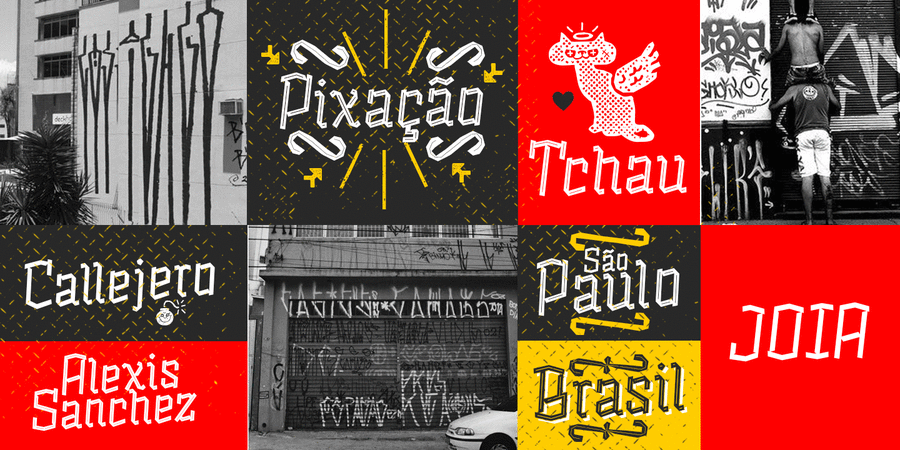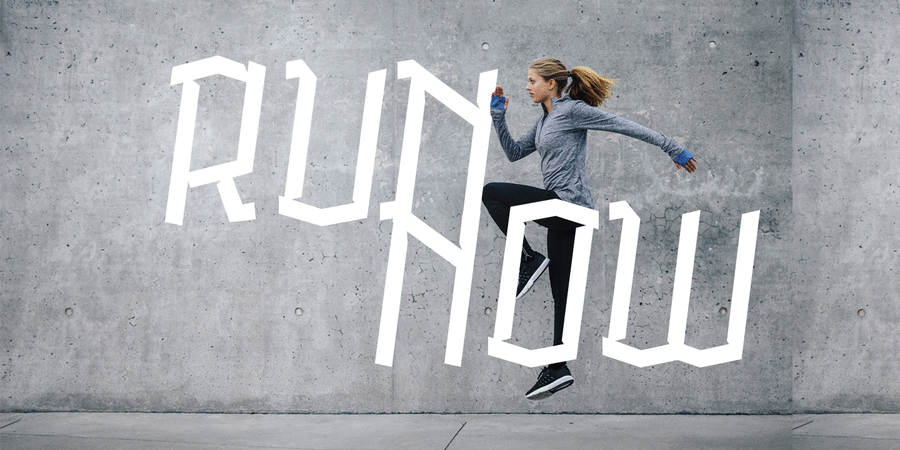
Шрифт за мотивами pixaçao або pichaçao — особливий жанр графіті, що виник в Сан-Паулу в 1980-і роки, хоча у 1960-ті роки вже існували подібні графіті проти військової диктатури, у контексті профспілкової боротьби. Це були протестні теги, намальовані смолою (порт. Piche — смола) на будівлях на великій висоті. У шрифті Alquitran (ісп. Alquitrán — дьоготь) цей унікальний вид літерації перероблений у дещо формальнішому стилі, додані різні накреслення з підтримкою багатьох мов, включно з кирилицею, та декоративні орнаменти. Шрифт розробили Родріго Арая Салас, Андрій Кудрявцев, Франциско Паєз у 2018 році.
різкий, хуліганський, експериментальний, тусовочний, клубний, екстремальний, ризикований, вуличний, грубий, сміливий, епатажний, ламаний, урбаністичний, агресивний, емоційний, яскравий, жорсткий, спекотний, кольоровий, південний, непосидючий, рухливий, активний, прикольний, крутий, молодіжний, оригінальний, характерний, виразний, грайливий, неохайний, андеграундний, гаражний, міський, дивний, дикий, помітний, живий, дозвільний, двіжняковий, гострий, чіткий, ремісничий, кустарний, крафтовий, твердий, ритмічний, студентськиий, сухий, революційний, небезпечний, зухвалий, артізанальний, екзотичний, вернакулярний, радикальний, запальний, недбалий, смачний, святковий, колючий, страшний, кричущий, макабричний, навіжений, божевільний, вибуховий, нервовий, прозорий, невагомий, легкий, крихкий, худий, тонкий, веселий, задерикуватий, смішний, доброзичливий, добродушний, радісний, привітний, пустотливий, дитячий, наївний, карикатурний, милий, мультяшний, дотепний, домашній, літній, затишний, усміхнений, щасливий, творчий, самобутній, артистичний, цікавий, декоративний, динамічний, колоритний, неформальний, неслухняний, рукотворний, натуральний, вигадливий, химерний, органічний, жартівливий, стрибучий, звіриний, брудний, побутовий, прямокутний, саморобний, хіпстерський, залізний, М'який, довірчий, добрий, позитивний, гладенький, статичний, свіжий, стиглий, простодушний, соковитий, симпатичний, пластмасовий, кучерявий, потішний, гулящий, нерівний, готичний, кріповий, старомодний, чарівний, чаклунський, магічний, фрік, окультний, таємничий, загадковий, зловісний, ролевий